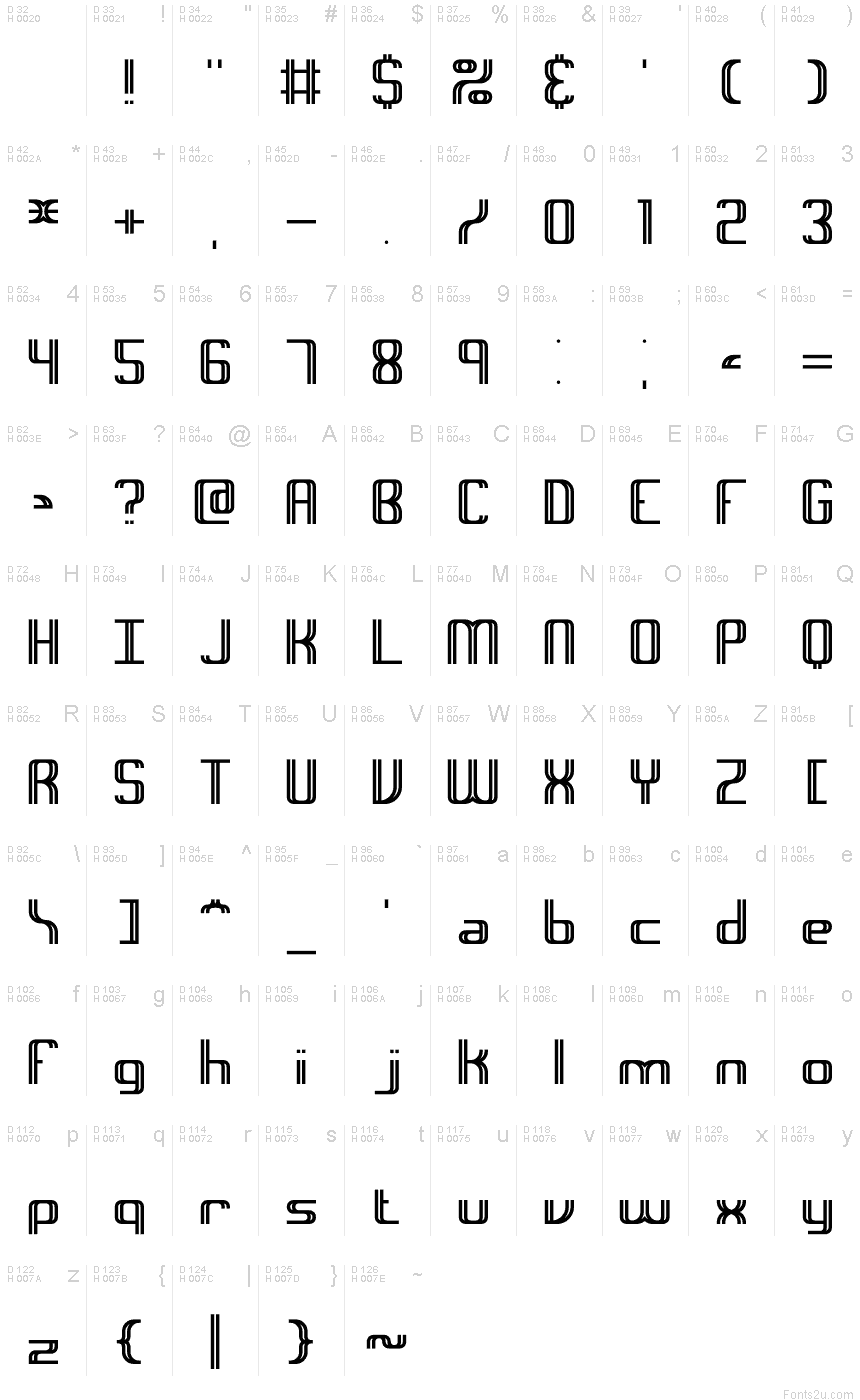
Intersect BRK von Aenigma Fonts ist eine kostenlose, moderne Display-Schriftart mit einer fast an Schaltkreise erinnernden Split-Line-Konstruktion, die jedem Wort einen technisch präzisen Charakter verleiht. Die hohen, röhrenartigen Striche verlaufen parallel und gehen in weiche, abgerundete Ecken über – für einen cleanen Techno-Vibe, der dennoch zugänglich und keineswegs kalt wirkt. Die Buchstaben sehen aus, als wären sie aus einem einzigen leuchtenden Draht geformt, was dem Text selbst in einfachem Schwarz-Weiß eine elegante, glühende Präsenz verleiht.
Mit Intersect BRK gewinnen fette Überschriften an Struktur und Rhythmus – ideal für Sci-Fi-Poster, Gaming-Logos, Tech-Event-Branding, Electronic-Music-Cover und experimentelle UI-Mockups. Diese kostenlose Schrift entfaltet ihre Wirkung besonders in großen Größen und mit etwas weiterem Zeilenabstand, damit die sich kreuzenden Striche atmen können. Kombinieren Sie sie mit einer schlichten geometrischen Sans für den Fließtext, um eine scharfe, futuristische Hierarchie zu schaffen, die sowohl gut lesbar als auch visuell beeindruckend ist.